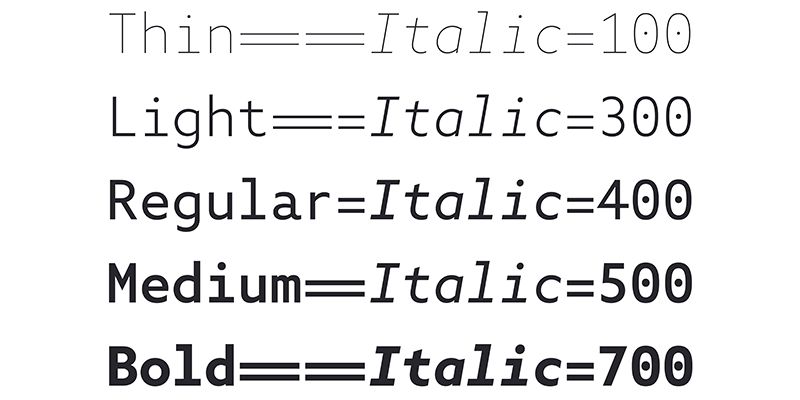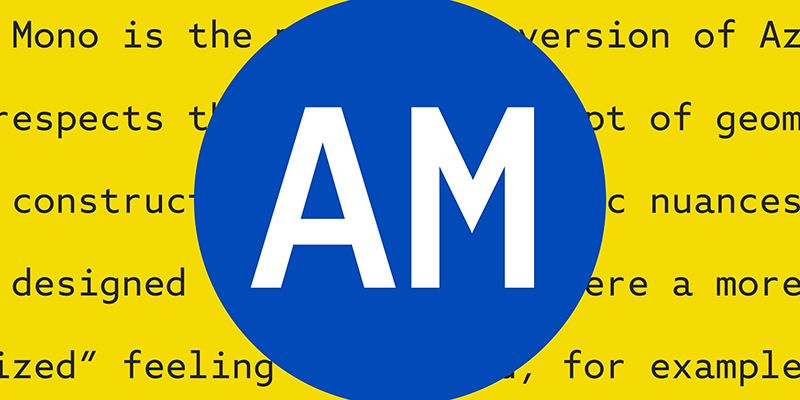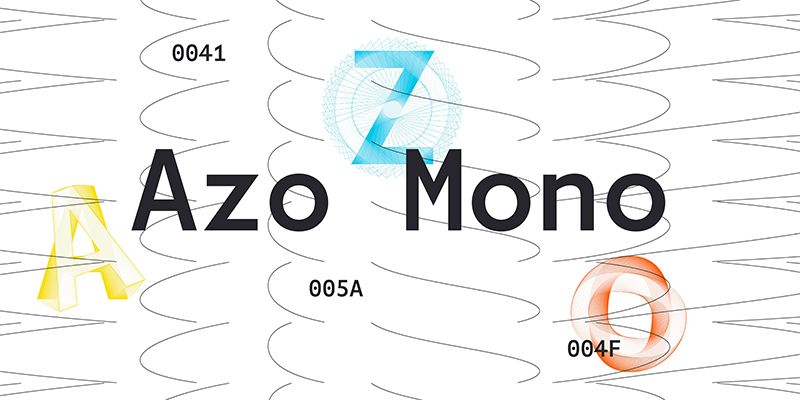
Azo Mono es la versión monoespaciada de Azo Sans. Respeta el concepto original de construcción geométrica con matices humanistas, pero se ha diseñado para situaciones en las que se busca un sentimiento más “deshumanizado”, por ejemplo, al presentar datos o escribir código.
Rui Abreu es diseñador gráfico y de tipos de letras portugués. Estudió Diseño Gráfico en la FBAUP (Faculdade de Belas Artes da Universidade do Porto), donde se graduó en 2003.
Paralelamente a su trabajo interactivo de diseñador para medios, Rui Abreu ha trabajado en fuentes comerciales desde 2006.